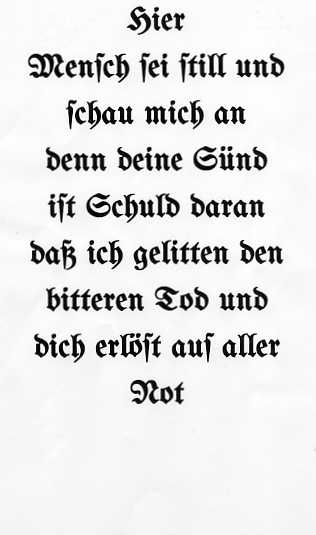
Hilfe!! Schrift gesucht!
ich würde mich freuen, wenn mir jemand aus diesem Forum auf der Suche nach dieser Schriftart weiterhelfen könnte.
Sie ist mir beim Formatieren meiner Festplatte leider verlorengegangen.
Nur zur Info: die Unifraktur Maguntia ist letztlich auch meine Mainzer, nur hat J. Mach Wust daraus einen Smartfont mit SIL Graphite und AAT Unterstützung gebaut.
Nein, nicht mehr, ich habe mittlerweile die meisten Glyphen neu digitalisiert.
Das ist meines Erachtens eine Schwabacher Fraktur.
Ich möchte nicht besserwisserisch erscheinen, aber die Bezeichnung
»Schwabacher Fraktur« verursacht mir Kopfschmerzen.
Hier nur ein Hinweis auf die »gute alte« Schriftklassifikation nach DIN 16518:
Die Gruppe X muß der klaren Unterscheidung wegen in fünf
Untergruppen gegliedert werden. Es sind dies:
Xa Gotisch, Xb Rundgotisch, Xc Schwabacher, Xd Fraktur,
Xe Fraktur-Varianten.
Die Schriftschnitte tragen vielfach diese Artbezeichnungen als
Zusatz zu ihren Namen, etwa Manuskript-Gotisch, Weiß-Rundgotisch,
Original-Schwabacher, Leibniz-Fraktur.
Also: Entweder Fraktur oder Schwabacher. Alles andere ist laienhaft ausgedückt!
Da dies aber eine Fraktur ist, wäre nur Schwabacher aber auch laienhaft ausgedrückt  8-)
Ich habe dich, glaube ich, nicht falsch verstanden, ich wollte nur präzisieren und sagen, dass Schwabacher hier genauso falsch ist wie der Begriff ›Schwabacher Fraktur‹ (der dann sogar doppelt ›falsch‹ ist).